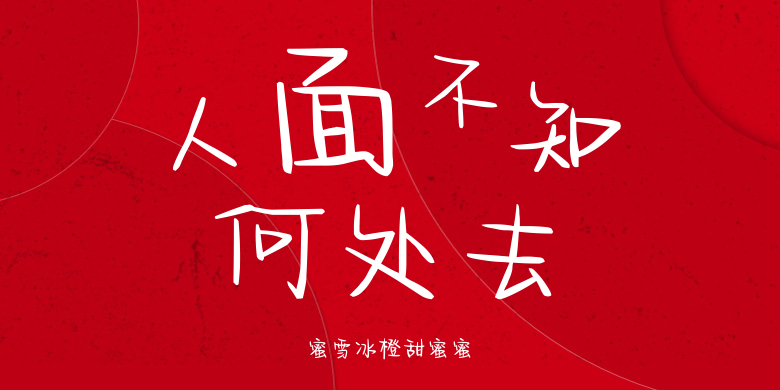
蜜雪冰橙甜蜜蜜
蜜雪冰橙甜蜜蜜,这款字体结构工整、笔画清晰,兼顾美观与易读性,适用于标题、正文、海报、包装、LOGO 等多种场景。字形优雅稳定,风格百搭耐看,适配日常排版与创意设计,让文字呈现更舒适、更具质感。蜜雪冰橙甜蜜蜜一笔一画,皆是细节,以均衡的比例、流畅的线条打造舒适视觉体验,字形端正大气,风格简约现代。无论是商业设计、品牌宣传还是日常排版,都能轻松驾驭,让文字更有格调与力量。蜜雪冰橙甜蜜蜜字体下载。